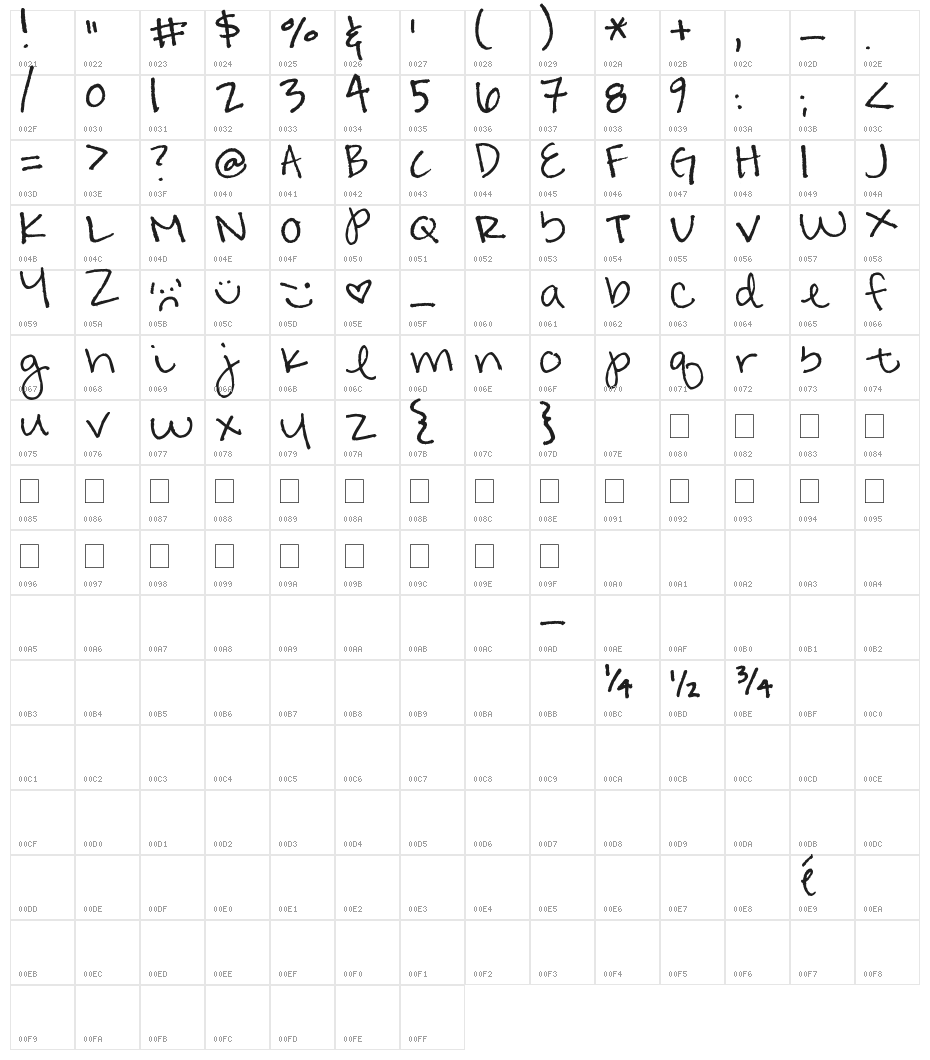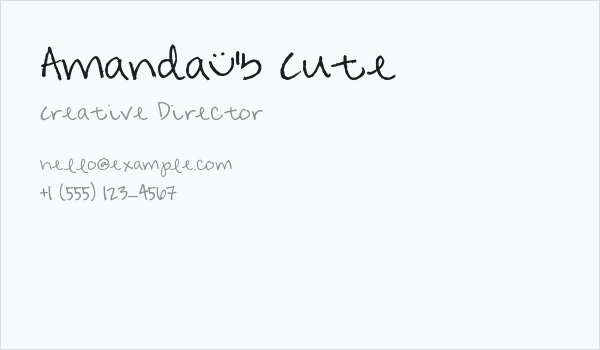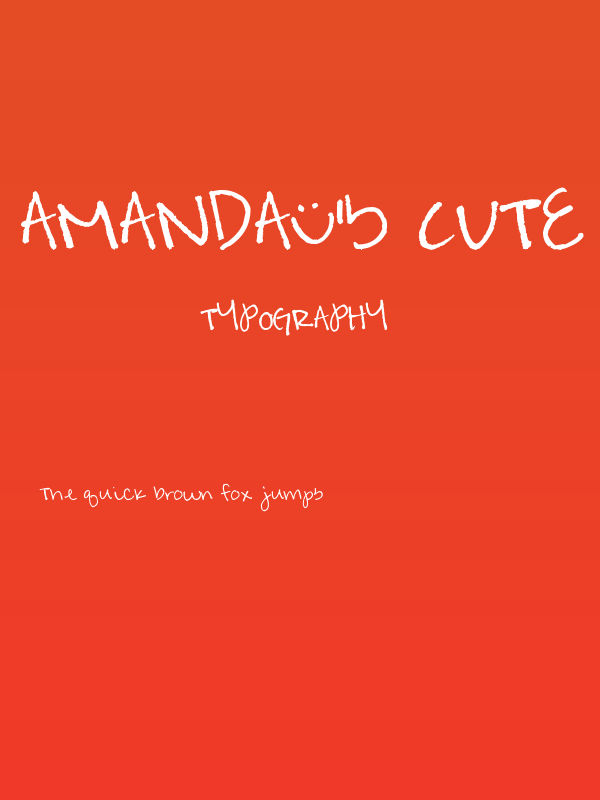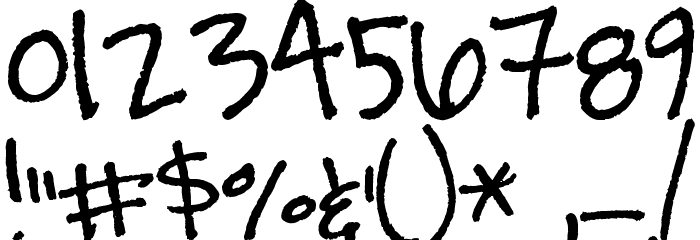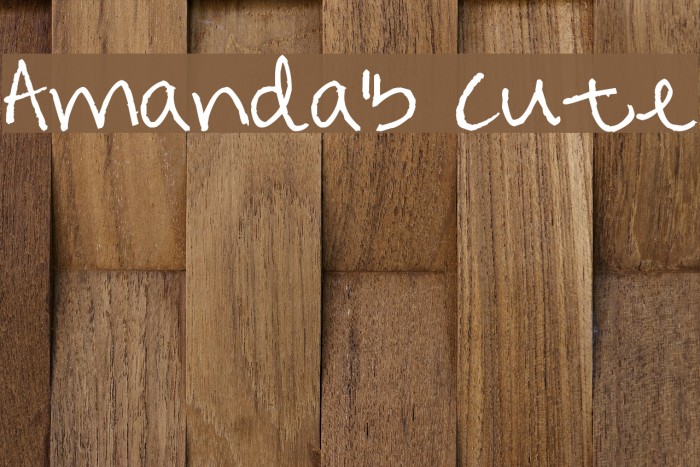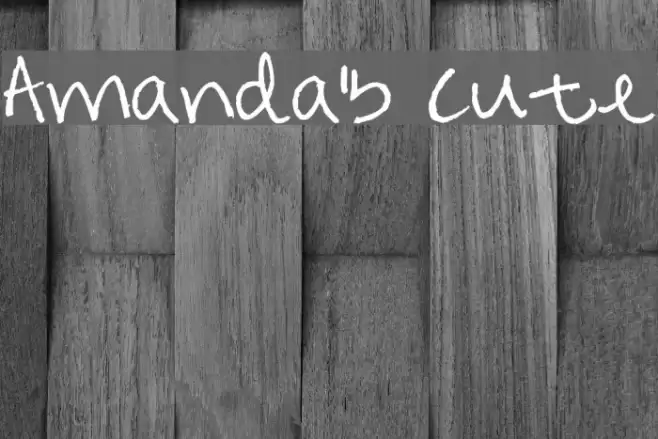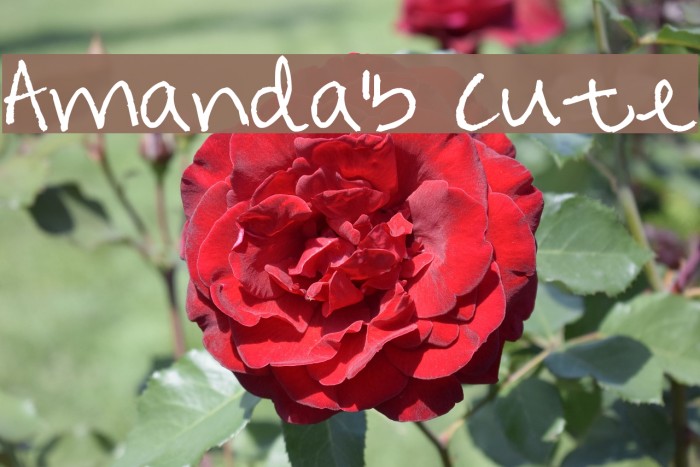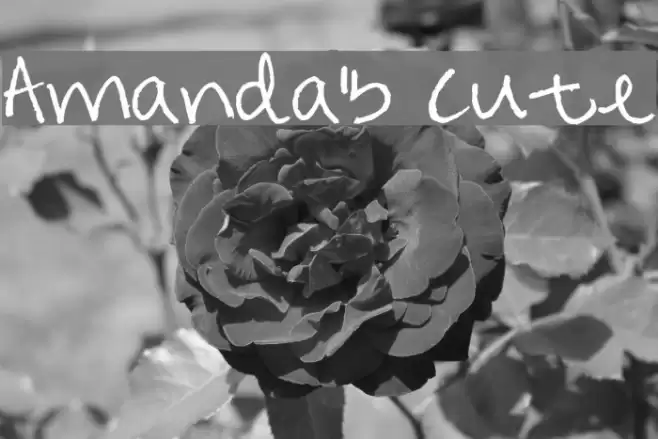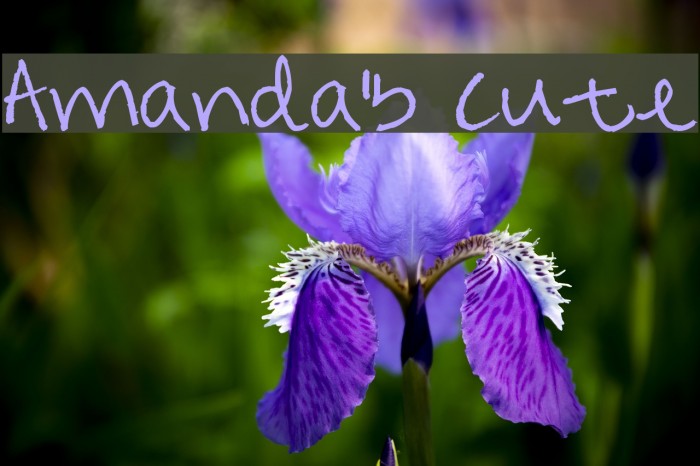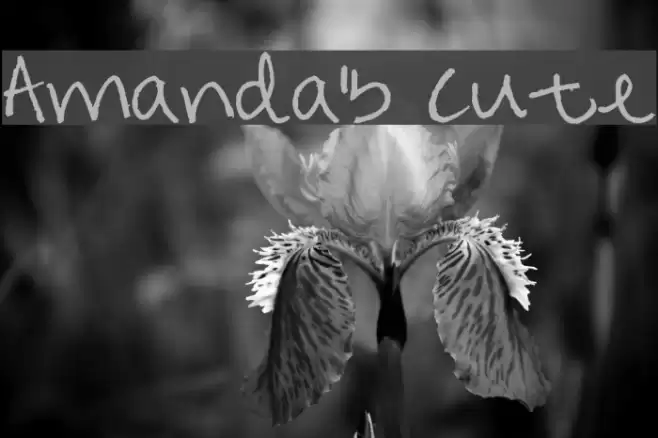
Amanda's Cute Font
| Estilo general | Casual, Playful |
| Caso de uso | Headlines, Informal text, Creative projects |
| Proyectos propuestos | Ideal for greeting cards, children's books, personal blogs, and creative branding projects. |